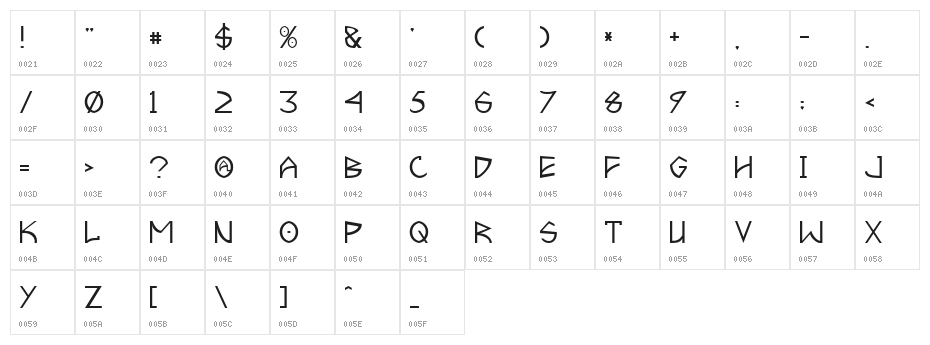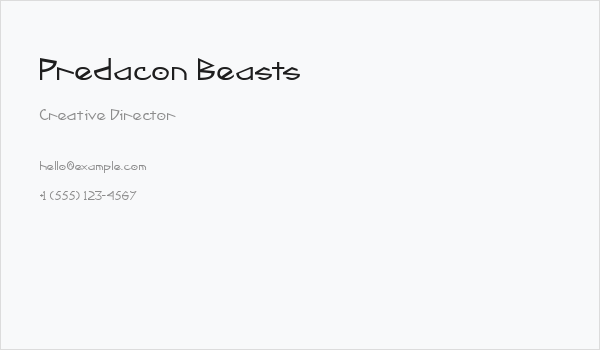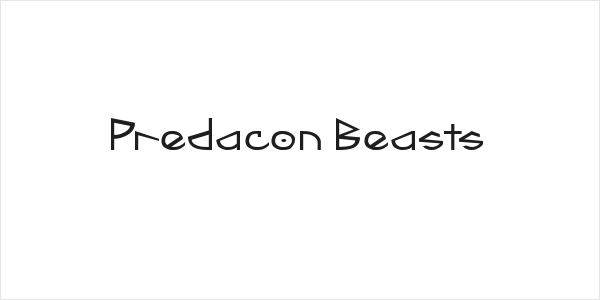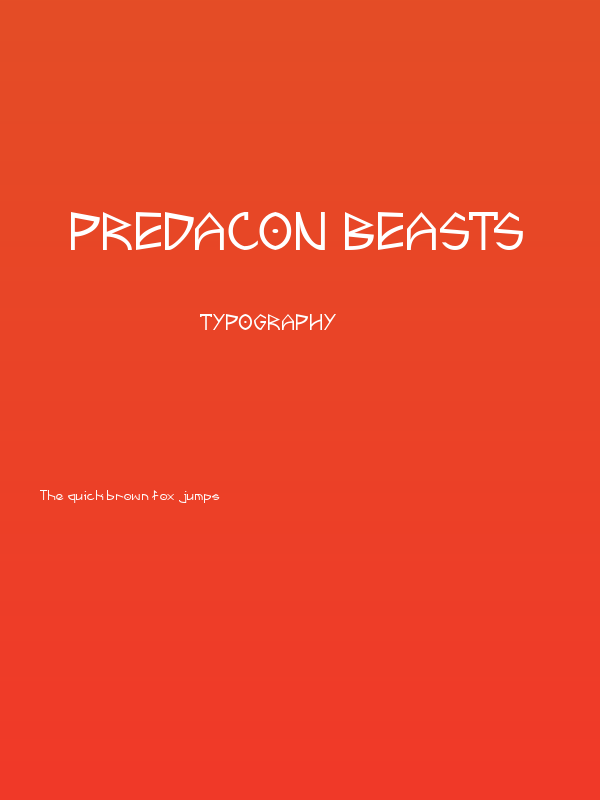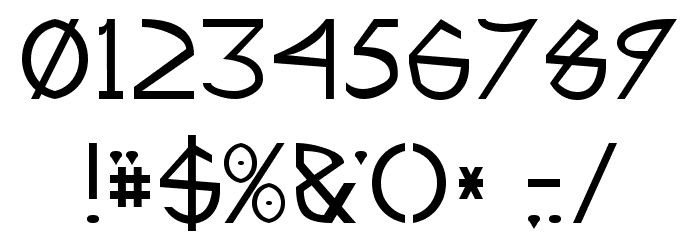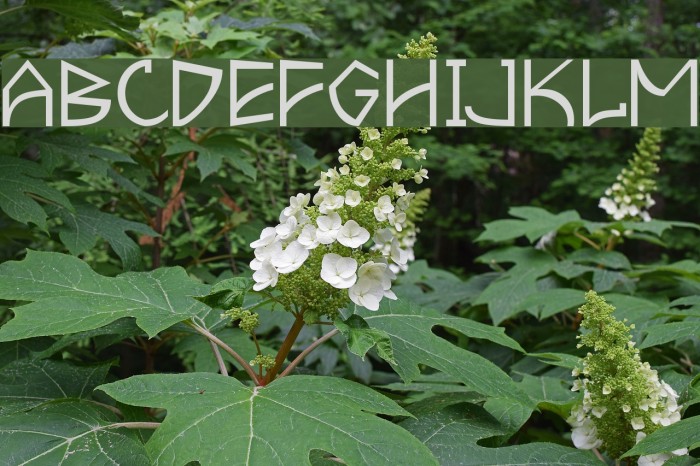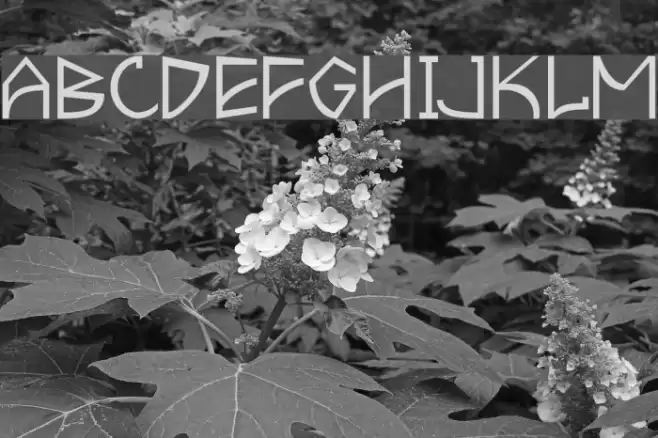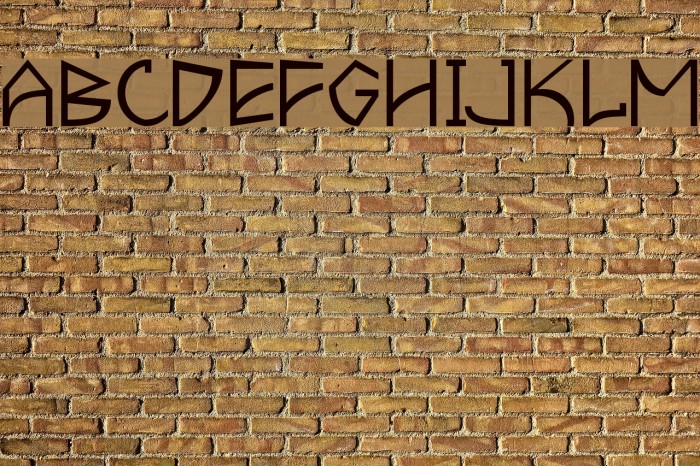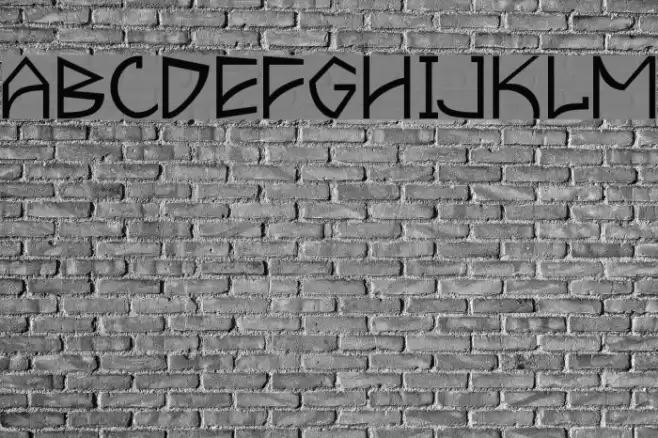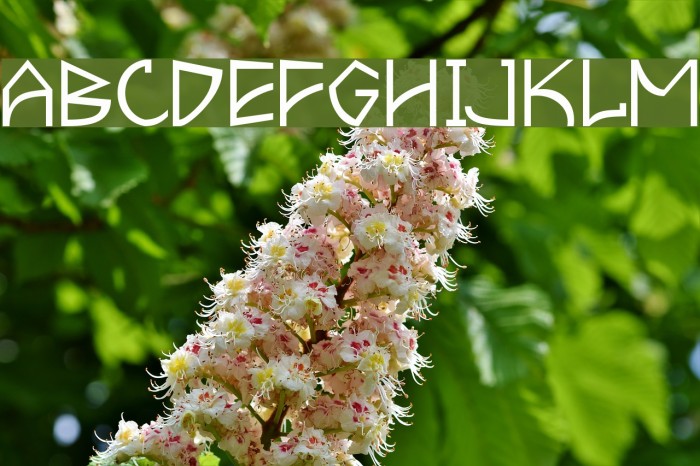
Predacon Beasts Font
| おすすめプロジェクト | Perfect for sci-fi themed projects, video game titles, posters, and branding that requires a modern and bold look. |